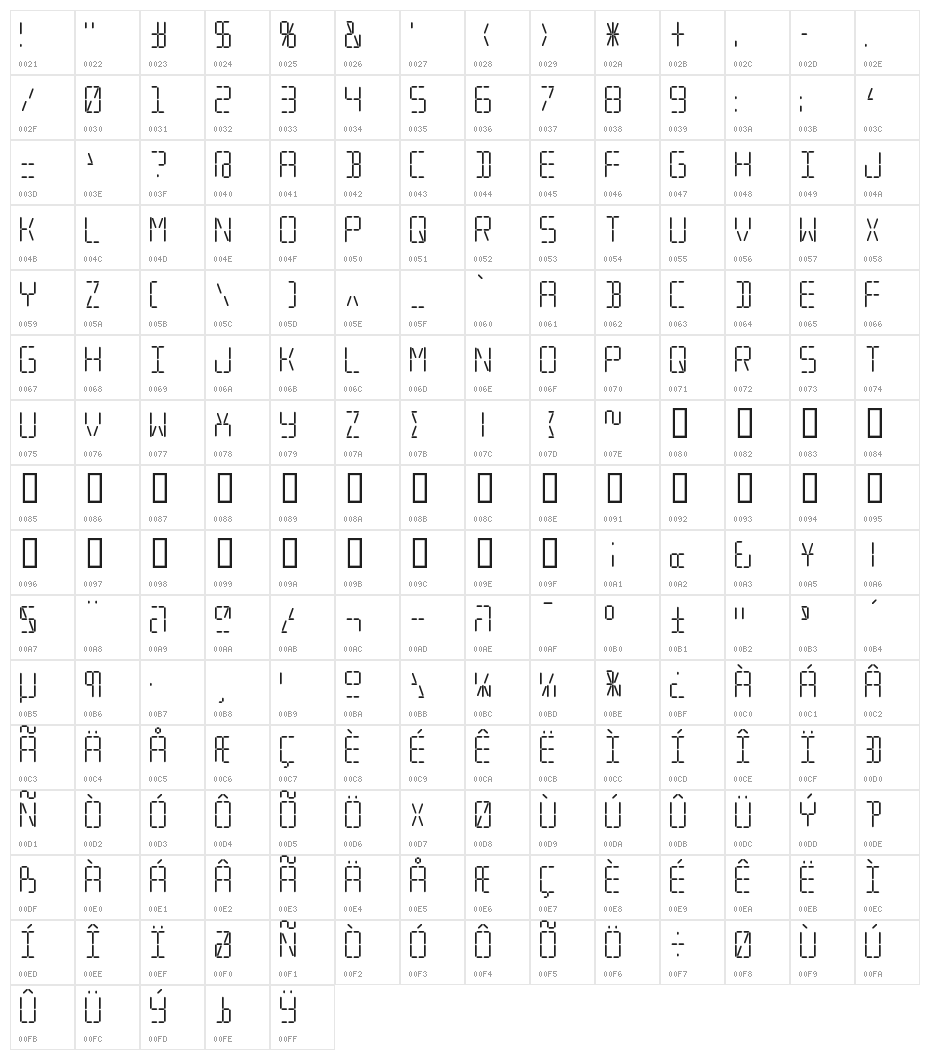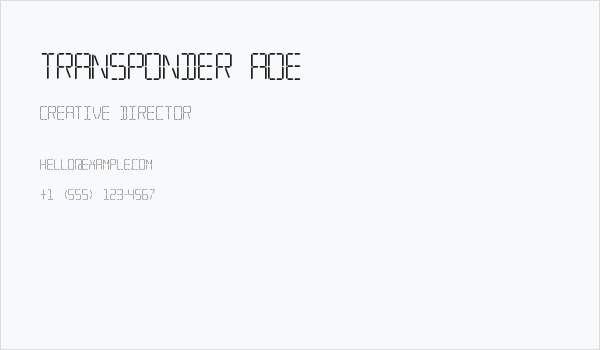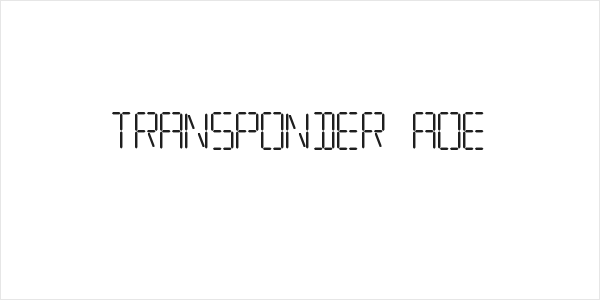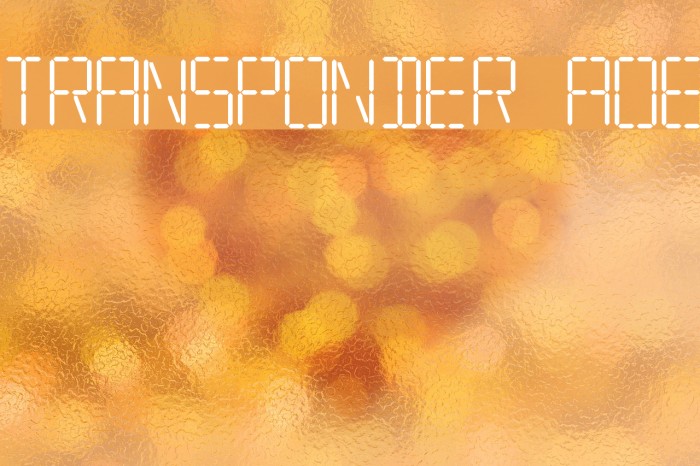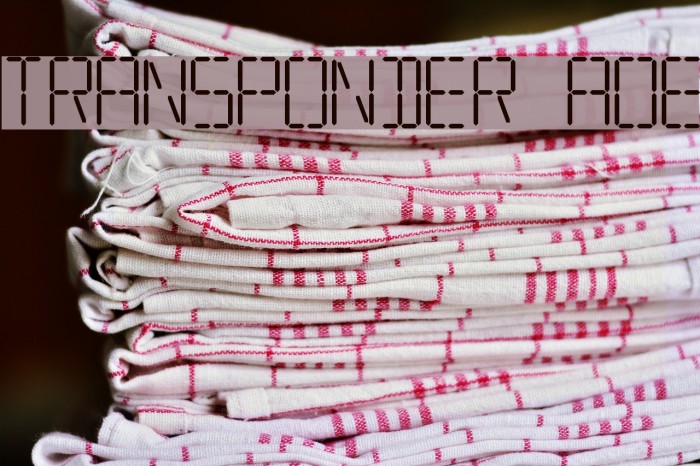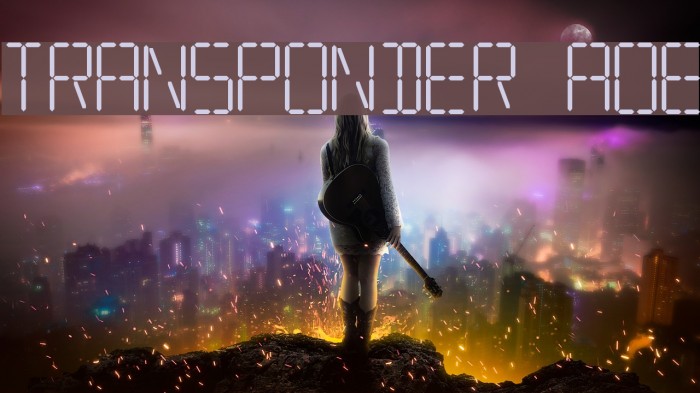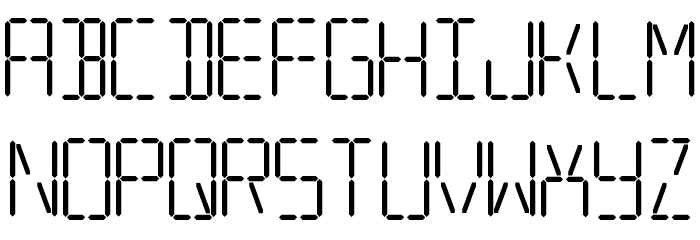
Transponder AOE Font
| Anwendungsfall | Headlines, Logos, Digital displays |
| Vorgeschlagene Projekte | Ideal for digital displays, tech-themed designs, futuristic branding, and electronic device interfaces. |